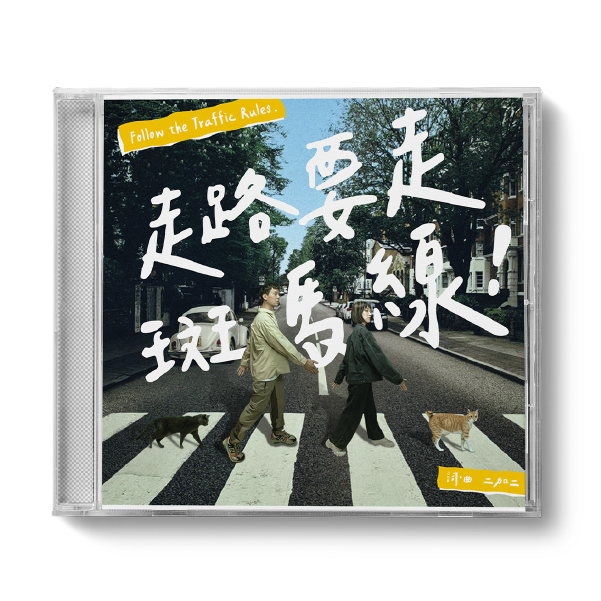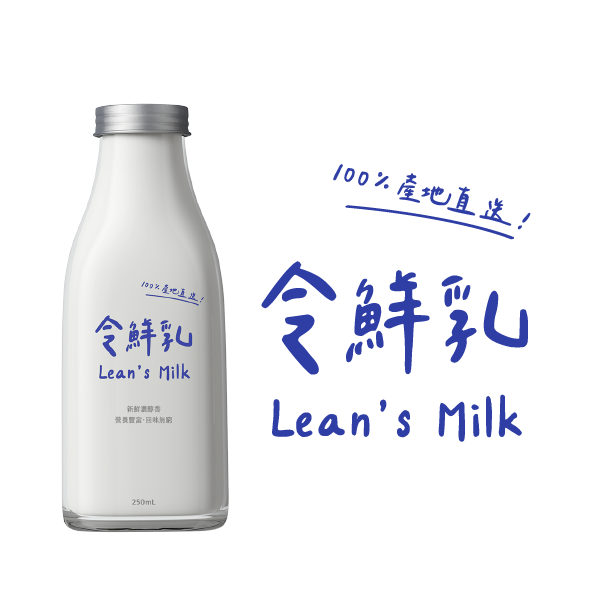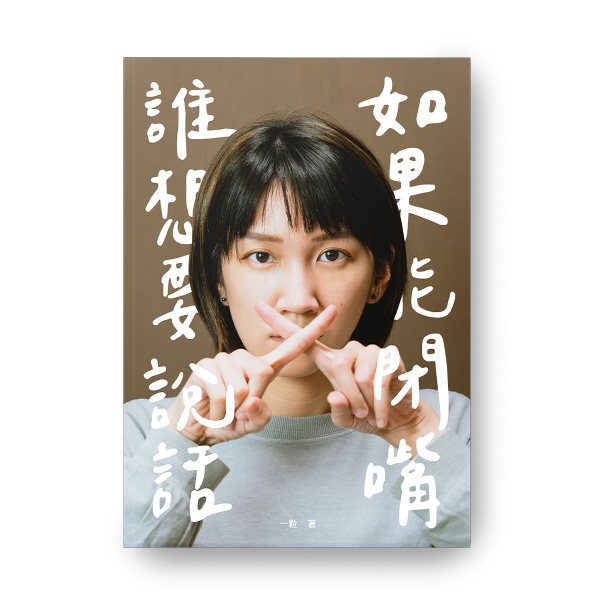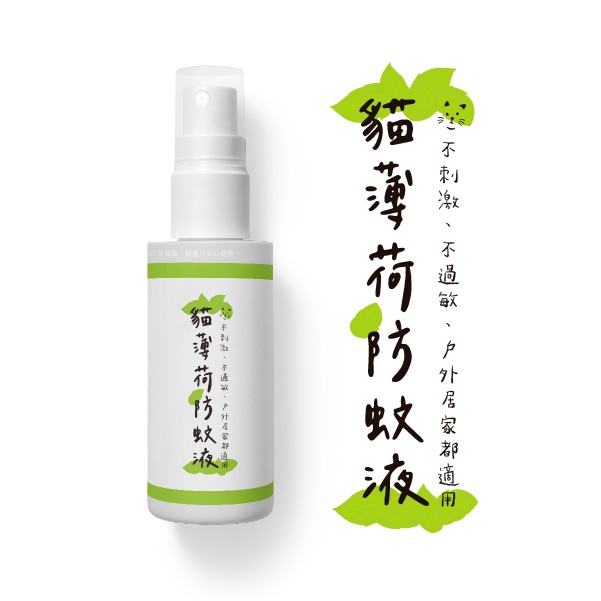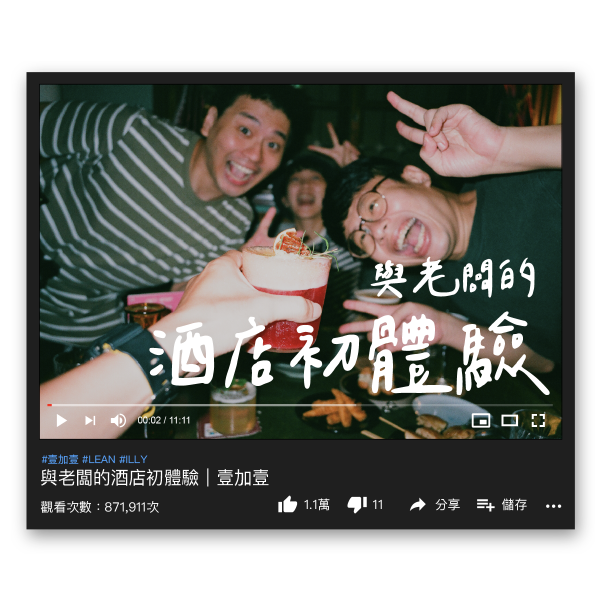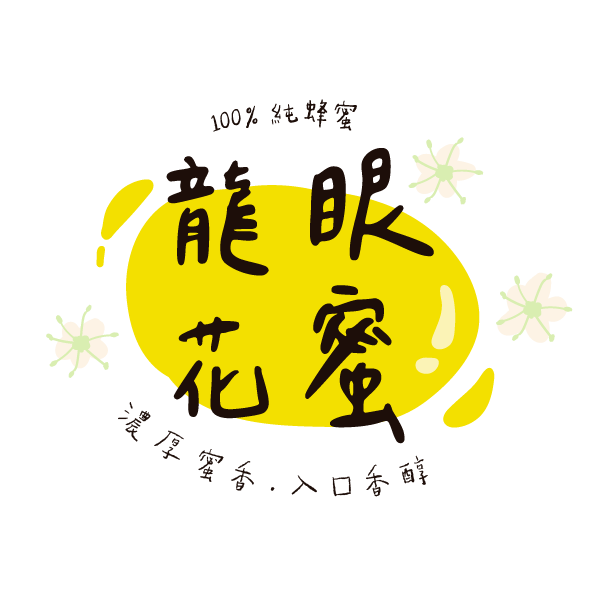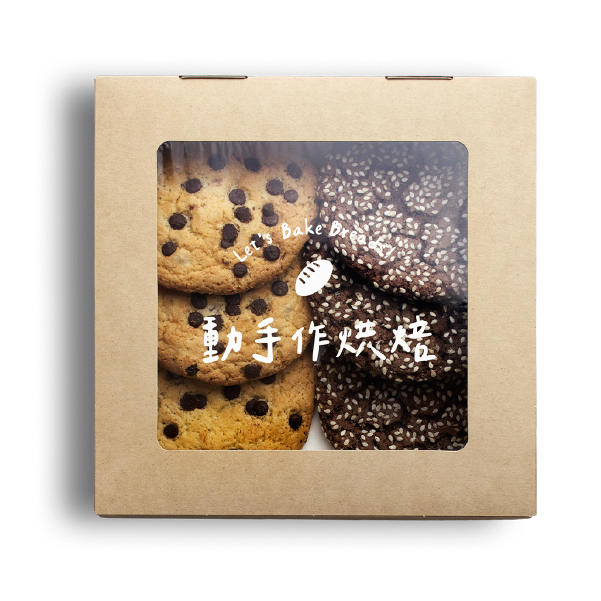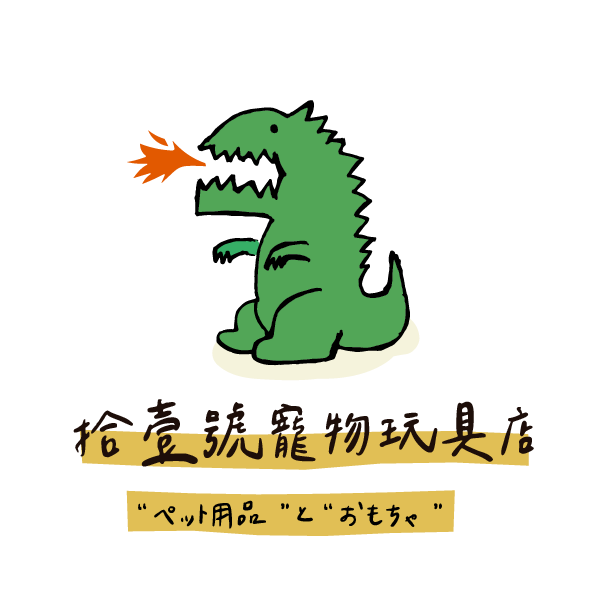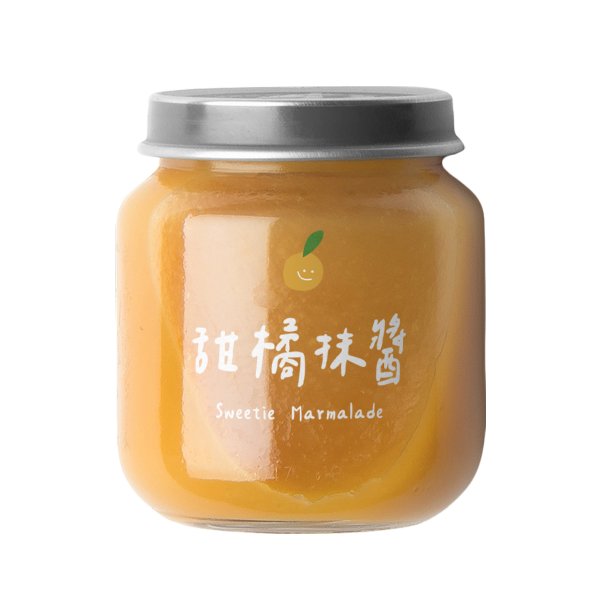
粒線體
一粒の手寫字爹斯!隨性不隨便,真誠不造作,看了就開心的字型!
字體採不等寬方式呈現,筆畫率性奔放,
適用於影片標題與各種產品標題中。
字型設計師
王一粒
王一粒,也就是 YouTuber 壹加壹的一粒,曾獲話劇社最佳女主角(?)封面文字藝術師,人稱一粒女神。每年都過 22 歲生日,真實年齡是個謎。自認為是 INFJ 怪人一個,但只要攝取的酒精夠多,就會變身 E 人。知名字體代表作包含「粒線體」與「粗線體」。